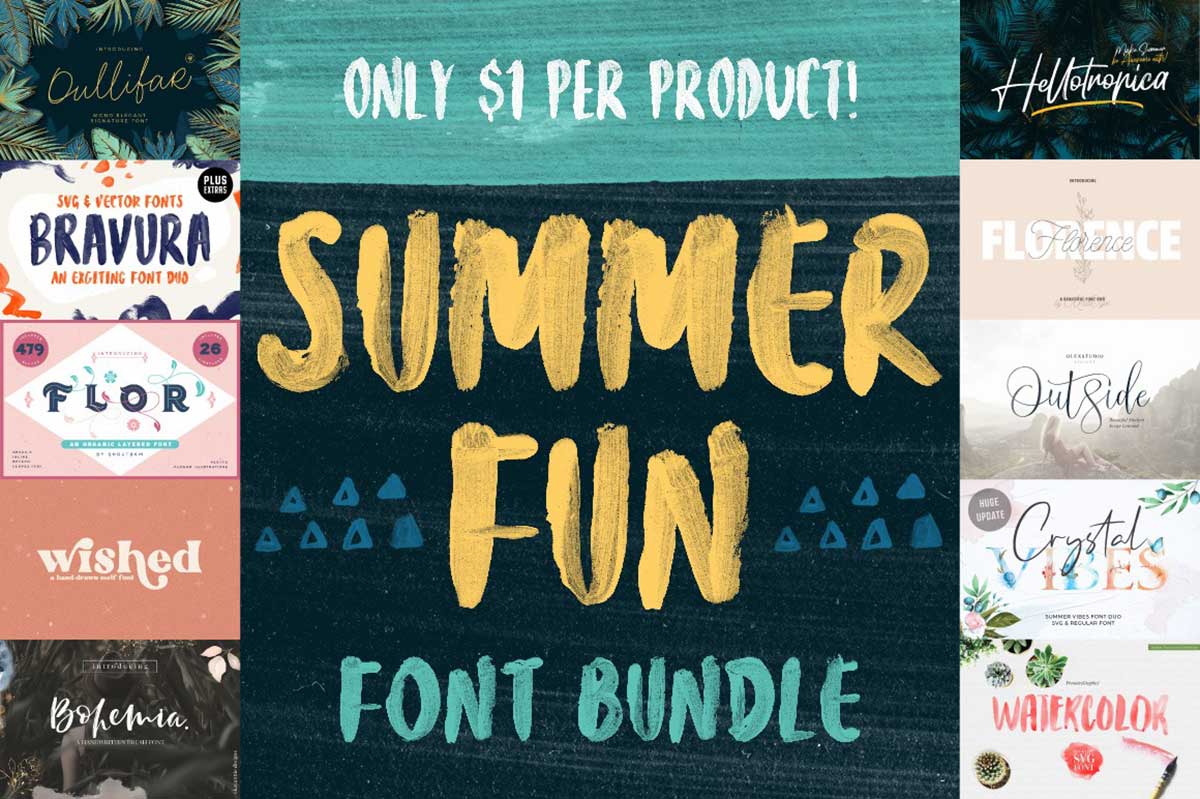
Pixel Surplusでは、フォント集「The Summer Fun Font Bundle(ザ・サマー・ファン・フォント・バンドル)」が一ヶ月限定販売中です。
手書き風のスクリプト書体やSVGフォントからユニークなデザインフォントまで、あなたのデザインに新しい風を吹き込む29セットを収録したコレクションです。Pixel Surplusでしか買えないオリジナルフォントもありますよ。
「The Summer Fun Font Bundle」の気になる中身
今回のバンドルの中で、私が特に気になるフォントはこちらです。
Bravura
派手な色使いで夏っぽい写真やイラストと組み合わせたい、ラフな手書き感が魅力の「Bravura」。SVGと通常のフォントが揃っているので、用途にあわせて使い分けられます。
Flor
「Flor」は植物のつるが伸びた飾りがついたフォントで、すべての文字に3種類のつるのパターンが用意されています。複数のパターンを自由に組み合わせて、あなただけのデザインを完成させましょう。
Crystal Vibes
植物をあしらったアルファベットがSVGフォントになった「Crystal Vibes」。ペアの手書きフォントと組み合わせれば、夏のラフな雰囲気をいっそう演出できます。ほかの植物素材も使えるものばかり!
Hamor Island
付属のイラストと組み合わせると、夏っぽいロゴや見出しがカンタンにできる「Hamor Island」。カジュアルな親しみやすさが、ユーザーとの距離を近づけてくれるフォントです。
Light Shutter
通常版、かすれ風、SVGの3種類のテクスチャがセットになった「Light Shutter」。写真やイラストに重ねて、大胆に使いたいフォントです。
このほか合計29セットを収録しています。この記事で紹介できなかった書体はぜひ詳細ページから確認してくださいね。